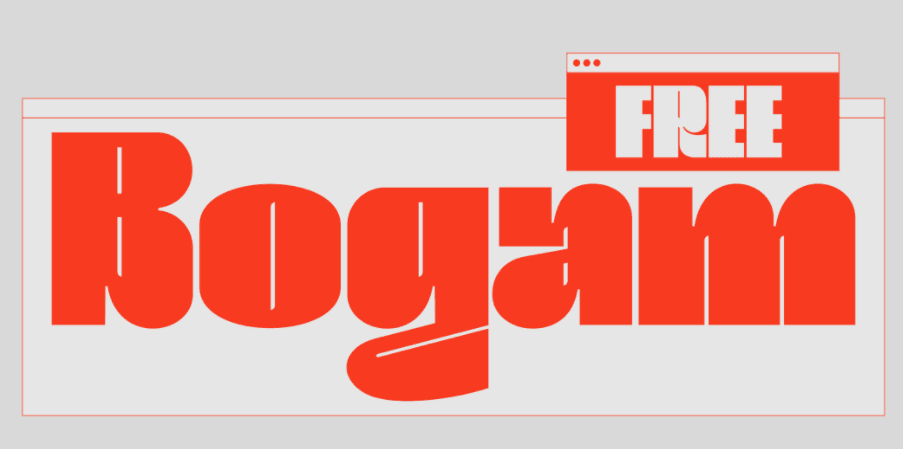
Bogam Display Sans Serif Font
Bogam - это новый бесплатный городской шрифт без засечек. Богам был вдохновлен городским стилем жизни, музыкой и модой. Bogam состоит из прописных и строчных букв, цифр и знаков препинания.